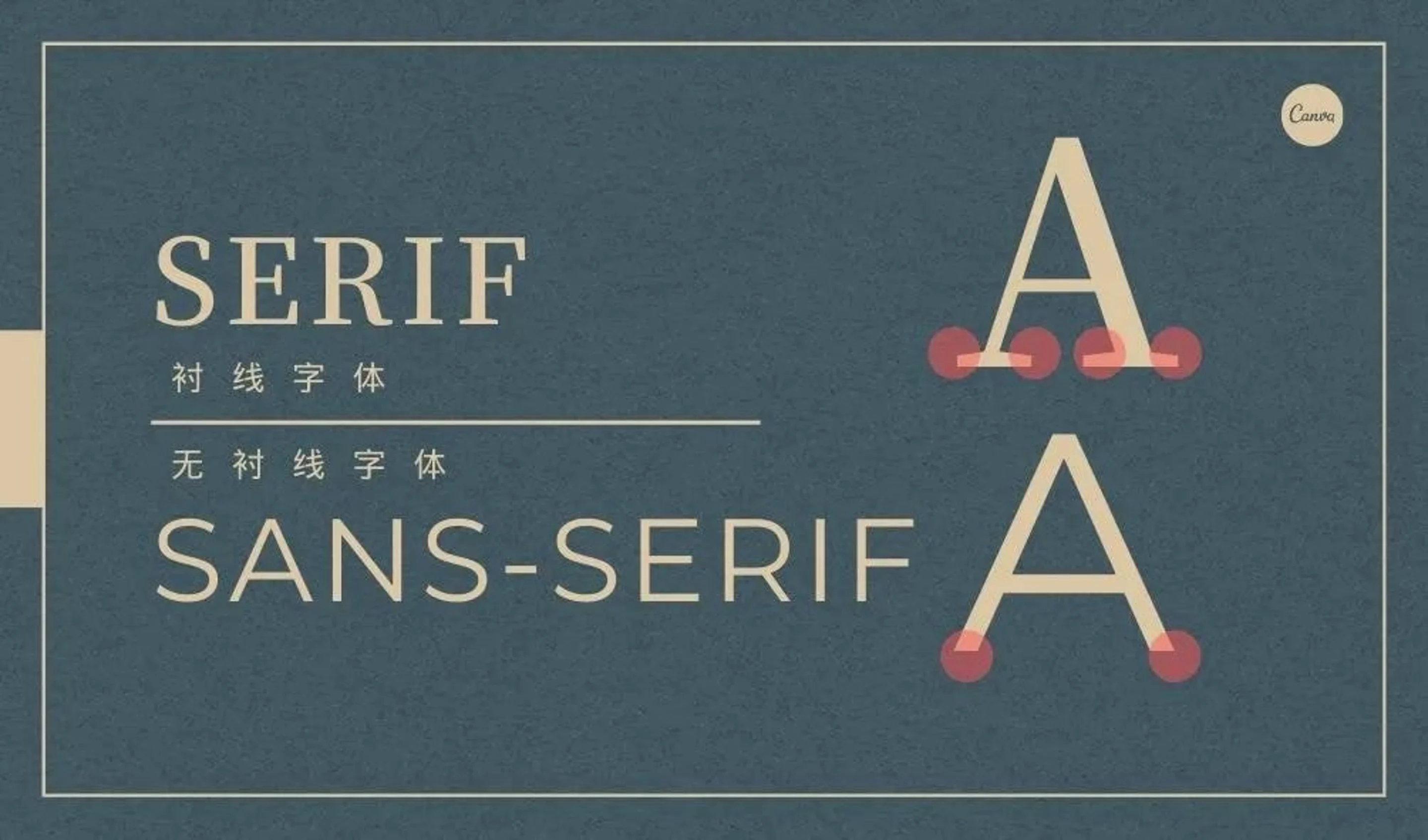
干货!长得差不多的英文字体,这样选就对了!
如果你平时要做PPT、视频封面图、海报⁠(在新标签页或窗口中打开)……那么一定会遇到一个不可避免的问题:如何选择合适的字体?
每一种字体都拥有独特的风格,字形的差异会带来不同的心理感受:现代、古典、厚重……今天我们就来聊一聊字体的分类,首先是英文字体的分类。
01 英文字体的分类
如果将英文字体进行分类,大致可以分为:衬线体、无衬线体、其他字体。
衬线体针对英文又有两种分类,一是分为:现代体和旧体;二是分为:支架衬线体、发丝衬线体、板状衬线体。
这种被称为「衬线」的装饰线的笔画设计,主流认为来源于古罗马纪念碑上的拉丁字母。
罗马字母被雕刻到石碑上之前,要先用方头笔刷写好样子,再照样雕凿。直接用方头笔刷书写会导致笔画的起始和结尾出现毛糙,所以在笔画开始、结束和转角时增加了收尾的笔画,也就自然形成了「衬线」。
而「衬线」和「无衬线」的区别,大致就是有笔锋和没笔锋的区别。
大家常用的一些经典字体,譬如Baskerville、Times New Roman,还有我个人比较喜欢用的Trajan,都属于衬线字体,能够体现传统、典雅、高贵和距离感。
因为衬线字体的落笔和结束都有额外的修饰,而且笔画的粗细有所不同,所以衬线字体比较容易识别,易读性也比较高。
在报刊杂志,整文篇幅较长的情况下,适合使用衬线字体进行排版。在进行换行阅读时识别度较高,可以有效避免行与行之间的阅读错误。
02 衬线字体的细分
衬线体又可以根据衬线变化分成三类:
具有特定曲线衬线的「支架衬线体」(bracket serif)
连接处为细直线的「发丝衬线体」(hairline serif)
厚粗四角形的「板状衬线体」(slab serif)
「支架衬线体」适合传统、复古、古典、史诗等图片风格,但也相对亲切。
像Baskerville、Times New Roman、Caslon、Georgia等都是比较常见的「支架衬线体」。
「发丝衬线体」具有明显的现代感,风格优雅,不适合磅值小的字体,适用于一些较为复古的时尚图片。
比较常见的字体有Didot,Bodoni。
「板状衬线体」常见于19世纪到20世纪的广告牌,多用于标题,同时也适合阳光活泼的怀旧图片风格。
除了上面的分法之外,衬线体也可以按照旧体和现代体进行分类。
由于电脑发明之前字体无法被数码化,所以类似手写的衬线体叫做“旧体”(old style),笔尖会留下固定倾斜角度的书写痕迹,其中最为明显的是:字母O较细部分的连线是斜线。
旧体并不意味着过时,当今的电脑已经将这种旧体数码化,而传统书籍的正文通常也用旧体排版,适合长文阅读。
比例工整,没有手写痕迹的衬线体叫“现代体”(modern style),O较细部分的连线是垂直的。
现代体体现了数码的精准和规范,给人以冷峻,严格的印象。由于衬线很细,该衬线体磅值缩小后文字易读性较差,一般在标题上使用。
无衬线字体则是相反的思路,它没有笔画首尾的装饰,所有笔画的粗细也接近相同。
03 无衬线字体
无衬线体在 80 年代开始兴起,在当时被称为 Grotesque(荒唐的)或 Gothic(哥特的)。
因为天然的技术感和理性气质,无衬线字体多为科技型企业所青睐,譬如目前苹果公司的官网采用的就是无衬线的San Francisco(英文)和苹方(中文)。
随着「简约美」理念开始风行,1957 年上市的 Folio、Helvetica 和 Univers 三个极具代表性的无衬线字型开始成为当代字型的主流。
无衬线字体适用的风格较多,优雅、高贵、极简、科技、商业……都可以使用无衬线字体,但是不同的字体之间会有细微的差别,这个在选择的时候需要注意。
个人常用的无衬线体Futura,这款字体在1927年由保罗·伦纳(Paul Renner)所设计发表。Futura的简约设计是由完美的圆形、三角形和正方形所组成,与20世纪30年代现代主义包豪斯运动相当契合。
尽管Futura字体诞生于一个世纪之前,但其设计看起来相当前卫且极具前瞻性,因此在各式设计中被广泛使用。
它甚至出现于广为流传的科幻电影海报上,譬如2013年的电影《地心引力》 以及艺术画廊的标志上。
写在最后
除了上面提到的这些字体种类,英文手写体也较为常见,但这种字体由于辨识度低,通常不作为标题使用,可在想要展现艺术感的场合作为装饰图案使用。